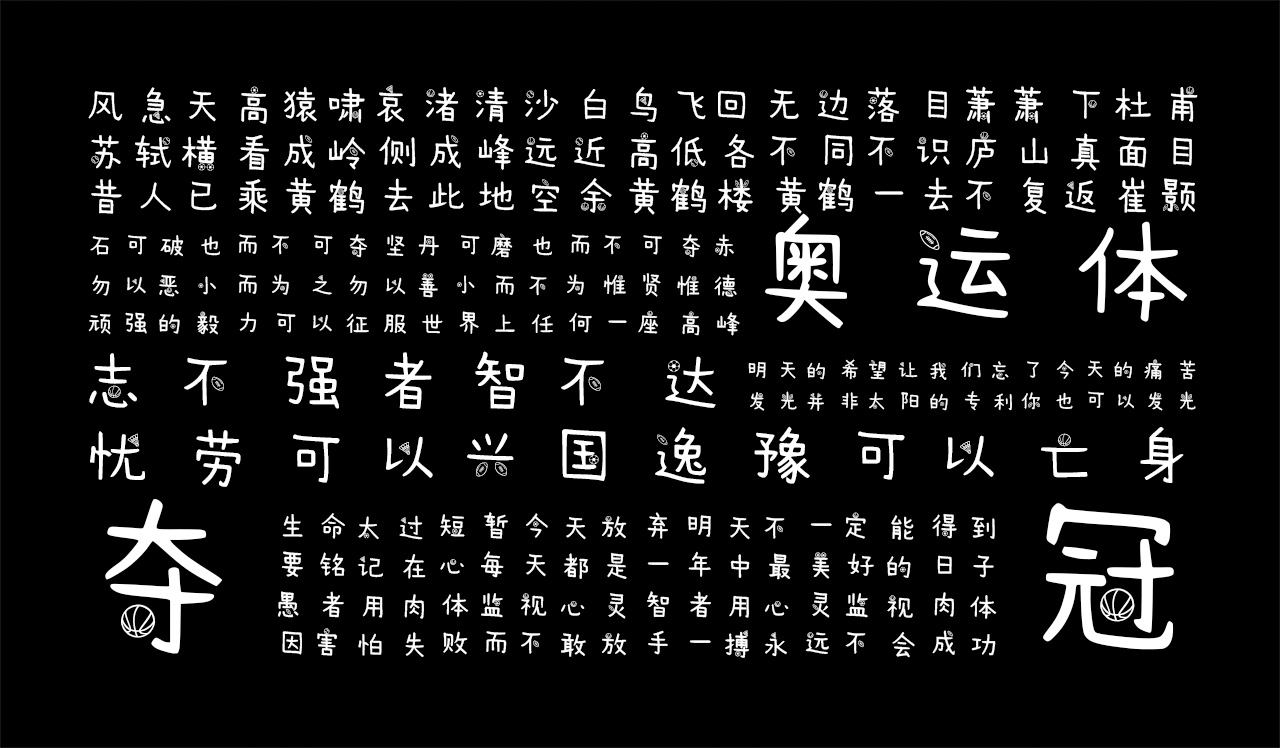
AI奥运字体
AI奥运字体,这款字体结构工整、笔画清晰,兼顾美观与易读性,适用于标题、正文、海报、包装、LOGO 等多种场景。字形优雅稳定,风格百搭耐看,适配日常排版与创意设计,让文字呈现更舒适、更具质感。AI奥运字体一笔一画,皆是细节,以均衡的比例、流畅的线条打造舒适视觉体验,字形端正大气,风格简约现代。无论是商业设计、品牌宣传还是日常排版,都能轻松驾驭,让文字更有格调与力量。AI奥运字体字体下载。
AI奥运字体是由ai制作完成的一款字体。
这是一款2024年8月5日下午通过直播30分钟制作的一款AI字体,同时将奥运会的中国健名也加入了一些在线的特定设计,比如陈芋汐,杨家玉、潘展乐等运动员的名字作了特别的设计。